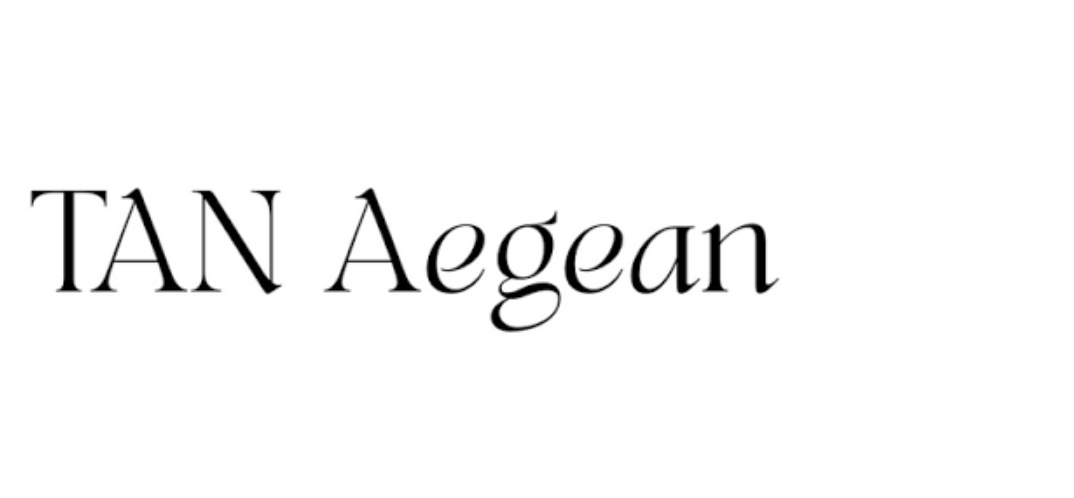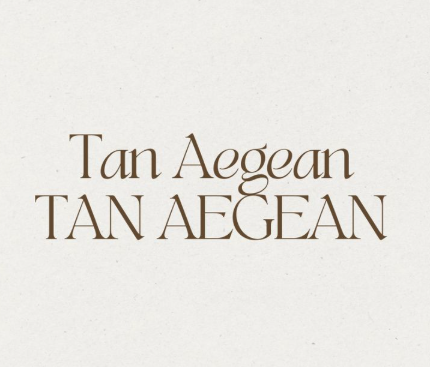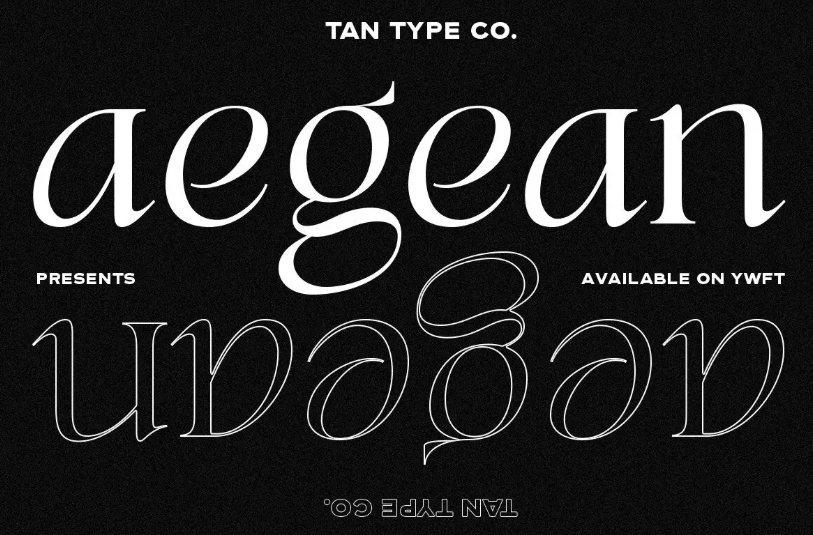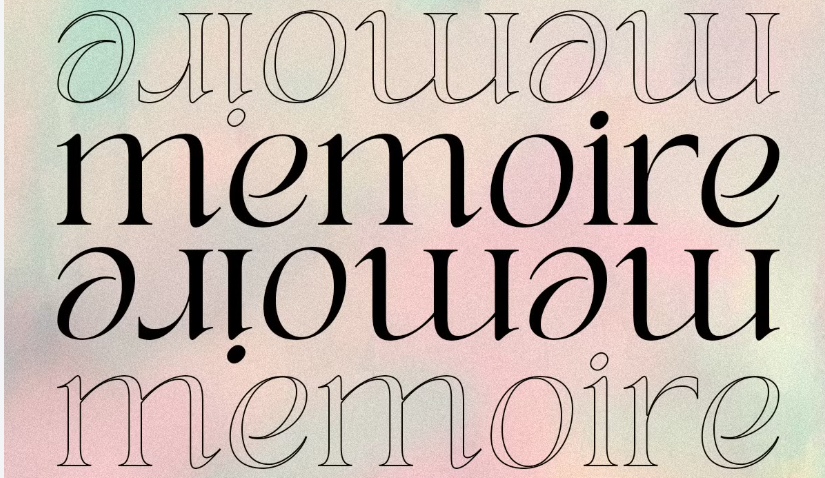
TAN Aegean Font Việt hóa là bộ phông chữ thuộc dòng Display Serif mang phong cách thời trang biên tập (Editorial) đầy độc bản, được sáng tạo bởi xưởng đúc chữ nổi tiếng TAN Type. Với sự kết hợp tinh tế giữa cấu trúc cổ điển, độ tương phản nét thanh đậm sắc sảo và những đường cong phá cách mang âm hưởng Địa Trung Hải, phông chữ này là lựa chọn đỉnh cao cho các thiết kế logo thời trang xa xỉ, nhãn chai nước hoa, bìa tạp chí nghệ thuật và bao bì hộp quà tặng thượng lưu. Doozypack.vn cung cấp link TAN Aegean Font Download chuẩn kỹ thuật, giúp bạn sở hữu phông chữ đẳng cấp từ Bộ Font TAN Type Việt hóa này, hỗ trợ đầy đủ tiếng Việt để tự tin thiết kế bao bì và bộ nhận diện thương hiệu chuyên nghiệp.
Đặc điểm thẩm mỹ độc đáo của bộ font TAN Aegean
TAN Aegean không đi theo sự khuôn mẫu của các phông chữ có chân truyền thống; nó mang đến một ngôn ngữ thị giác đầy tính duy mỹ, nghệ thuật và mang đậm dấu ấn cá nhân.
Phong cách Editorial Serif mang hơi thở Địa Trung Hải độc bản
Đặc trưng lớn nhất của TAN Aegean Font Việt hóa là tỷ lệ chữ thanh thoát kết hợp cùng các chi tiết chân chữ (serif) biến tấu vô cùng độc đáo. Cấu trúc chữ gợi liên tưởng đến những kiến trúc cổ đại vùng Địa Trung Hải, mang lại cảm giác phóng khoáng, lãng mạn nhưng vô cùng quyền lực. Khi đặt TAN Aegean làm tiêu đề trên bao bì, sản phẩm của bạn sẽ ngay lập tức toát lên vẻ ngoài đắt tiền, thời thượng và mang tinh thần của các kinh đô thời trang lớn.
Những đường cong phá cách và ký tự thay thế nghệ thuật
Các ký tự trong TAN Aegean Regular Font Free Download sở hữu những điểm uốn lượn bất ngờ ở các chữ cái đặc thù, tạo nên một nhịp điệu Typography vô cùng cuốn hút. Kho ký tự thay thế (Alternates) phong phú cho phép bạn dễ dàng tùy biến để tạo ra những biểu tượng logo hoặc tiêu đề bao bì không đụng hàng với bất kỳ ai.
Ưu điểm nổi bật của bộ Font TAN Type Việt hóa
Khi ứng dụng các phông chữ độc quyền từ nước ngoài vào thị trường trong nước, sự chỉn chu về dấu câu là yếu tố quyết định đến tính chuyên nghiệp của ấn phẩm:
- Khắc phục triệt để lỗi dấu tiếng Việt: Phiên bản Font Việt hóa TAN đã được đội ngũ thiết kế trau chuốt thủ công từng dấu câu. Các dấu sắc, huyền, hỏi, ngã, nặng được vẽ thanh mảnh đồng nhất cùng thân chữ gốc, không gây cảm giác chắp vá hay làm đè nét làm mất tính thẩm mỹ editorial.